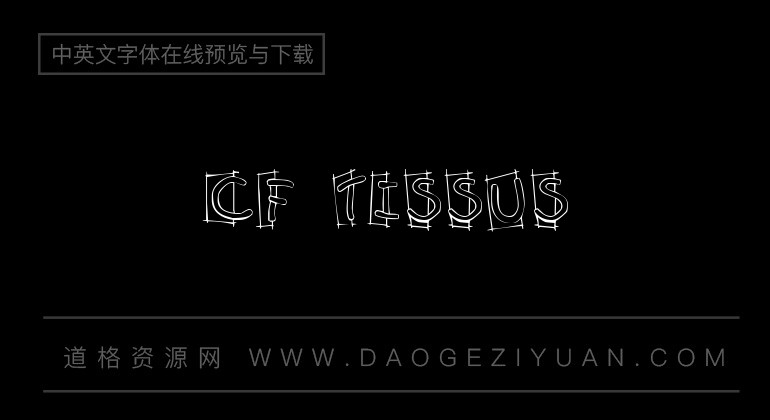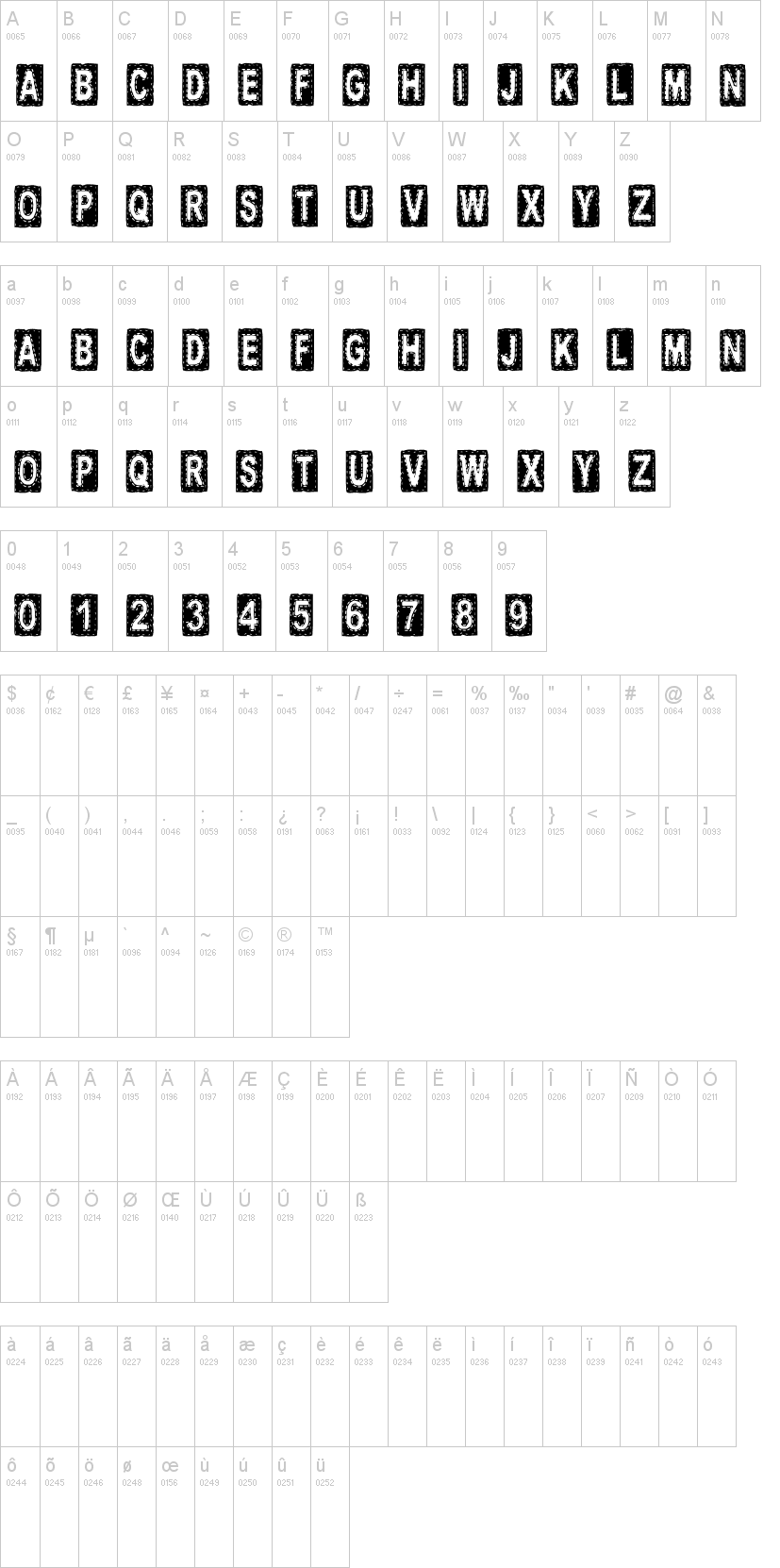
CF Tissus
CF Tissus 是一款由 Charles Fréger 创建的字体,它是一款抽象类型的字体,具有独特的外观和感觉。它具有抽象的线条,细节丰富,并且具有清晰的结构感。它可以用于任何类型的设计,特别适合用于印刷、网页和图形设计。CF Tissus 是一款具有极强表现力的字体,可以用来创造出精美的作品。
CF Tissus是一款非常不错的手写艺术字体,具有很好的视觉感,适合于文化类的宣传设计、商业类品牌的广告和产品包装设计以及个性化文字排版等较多场景。
CF Tissus字符映射图